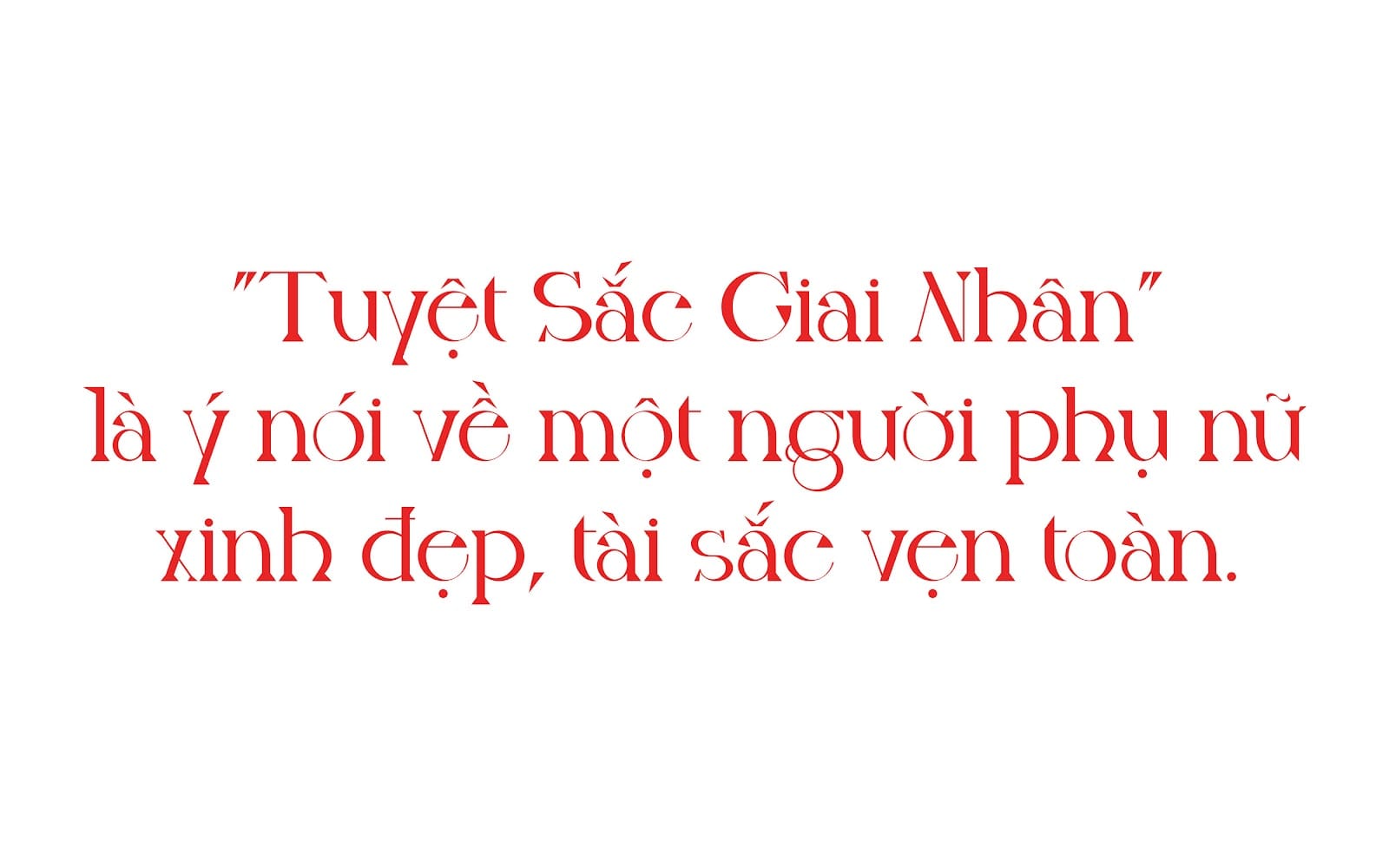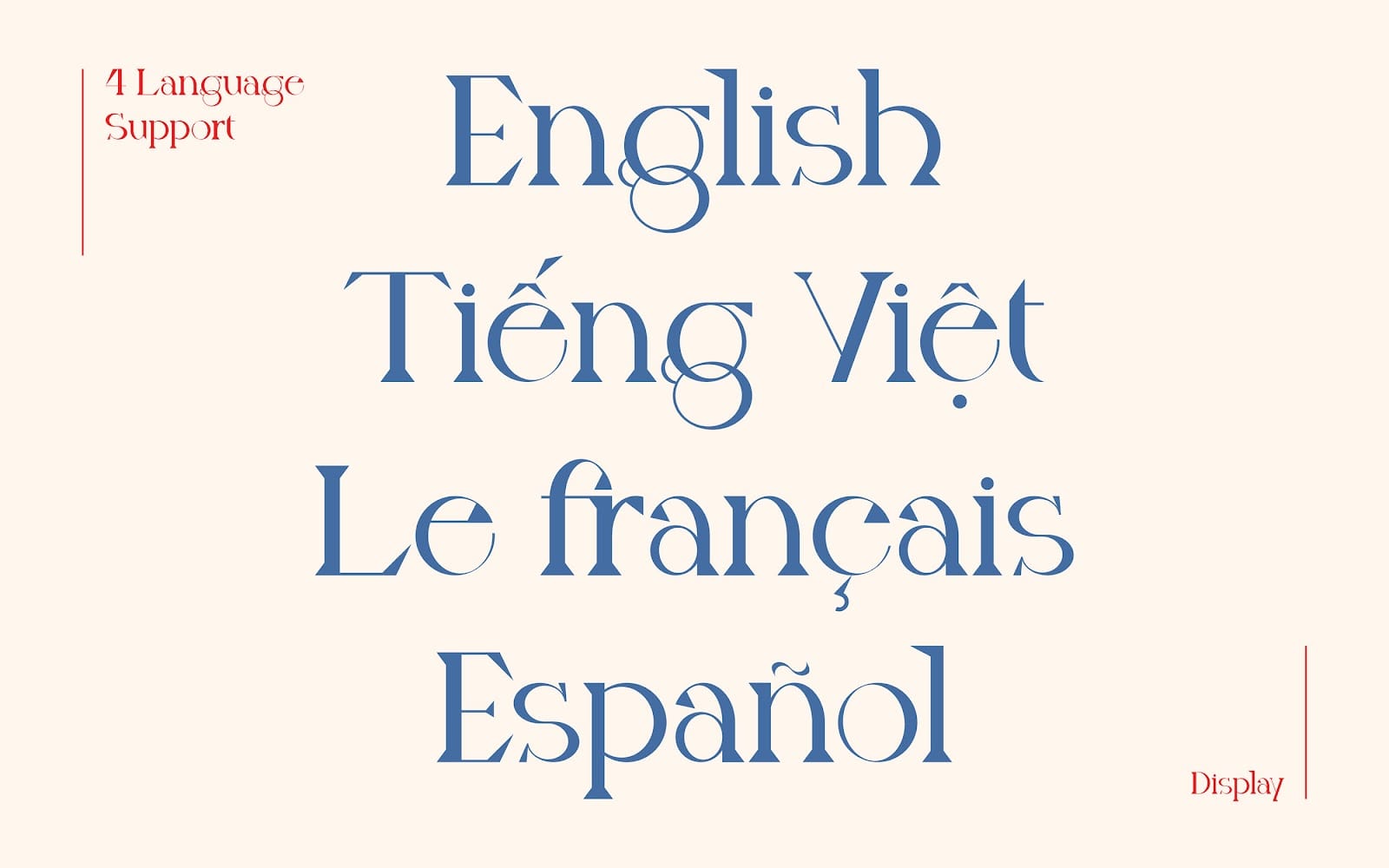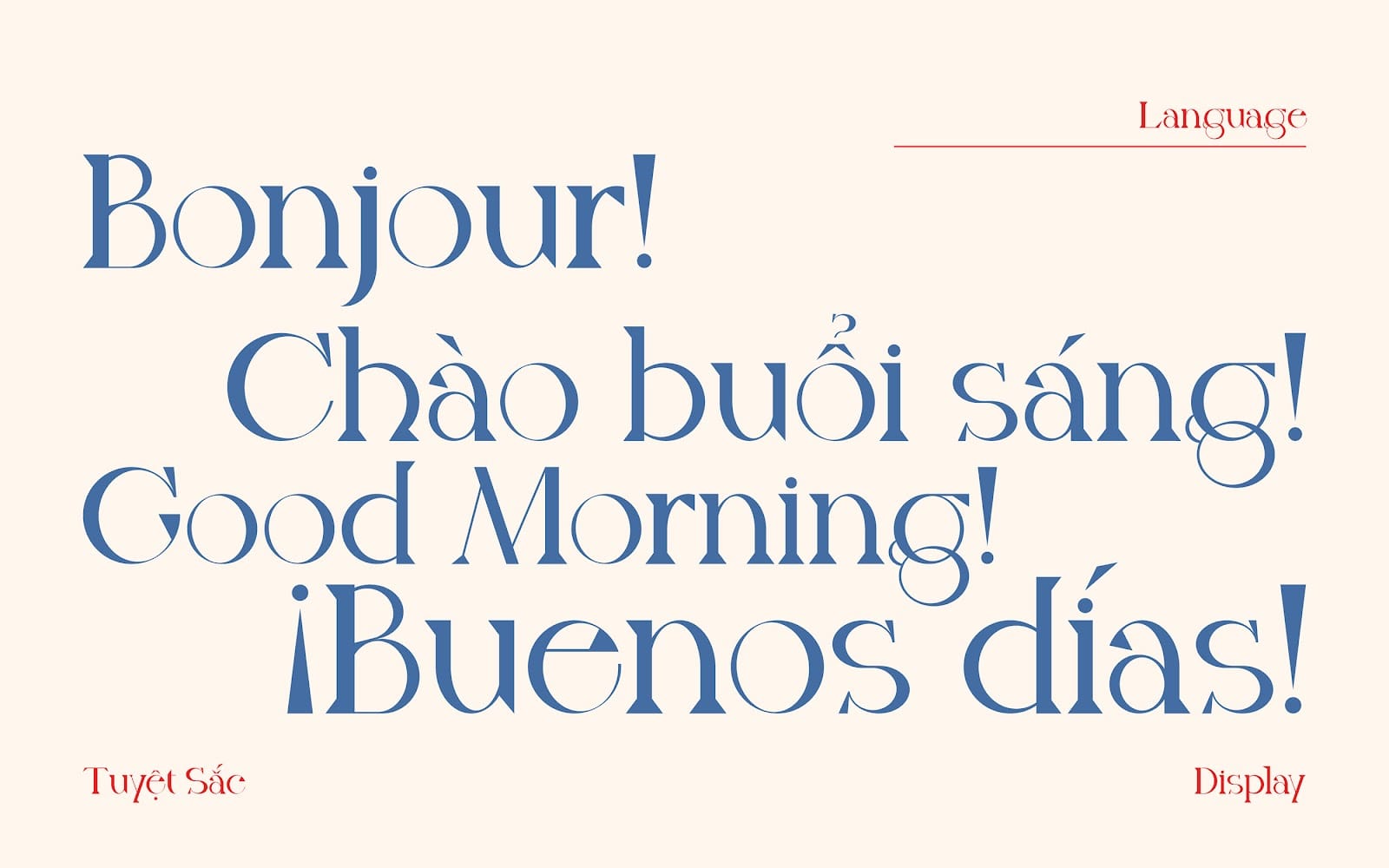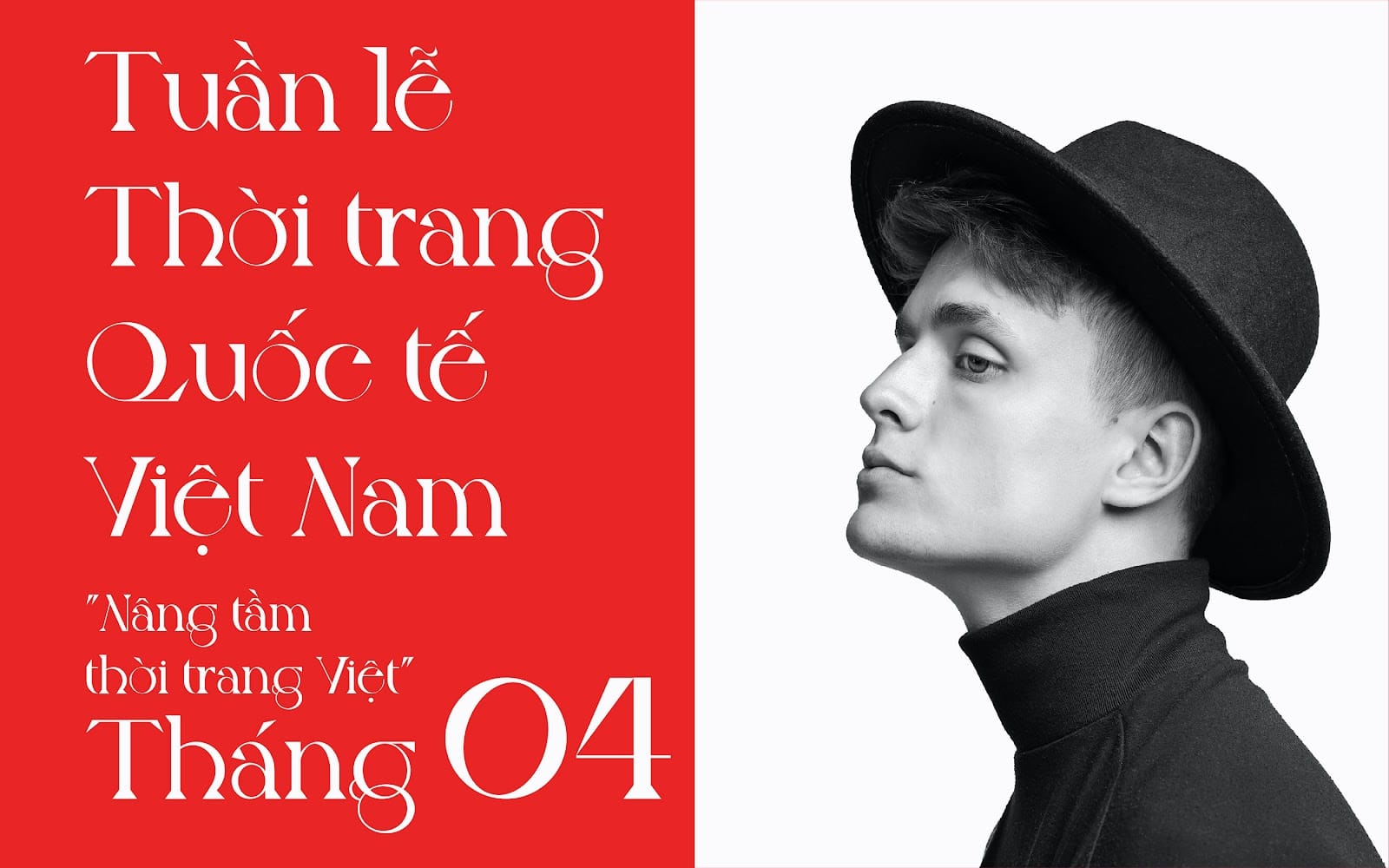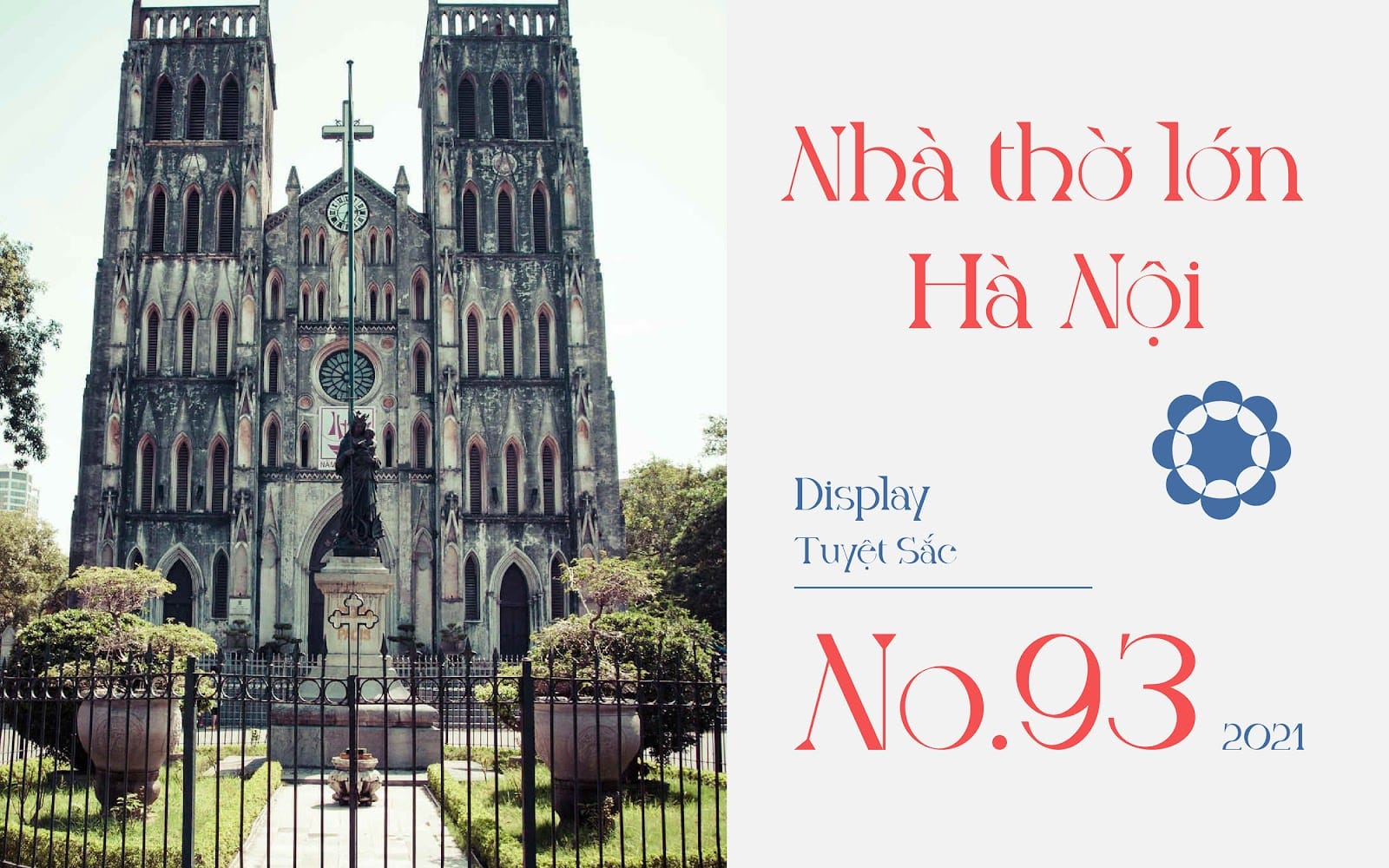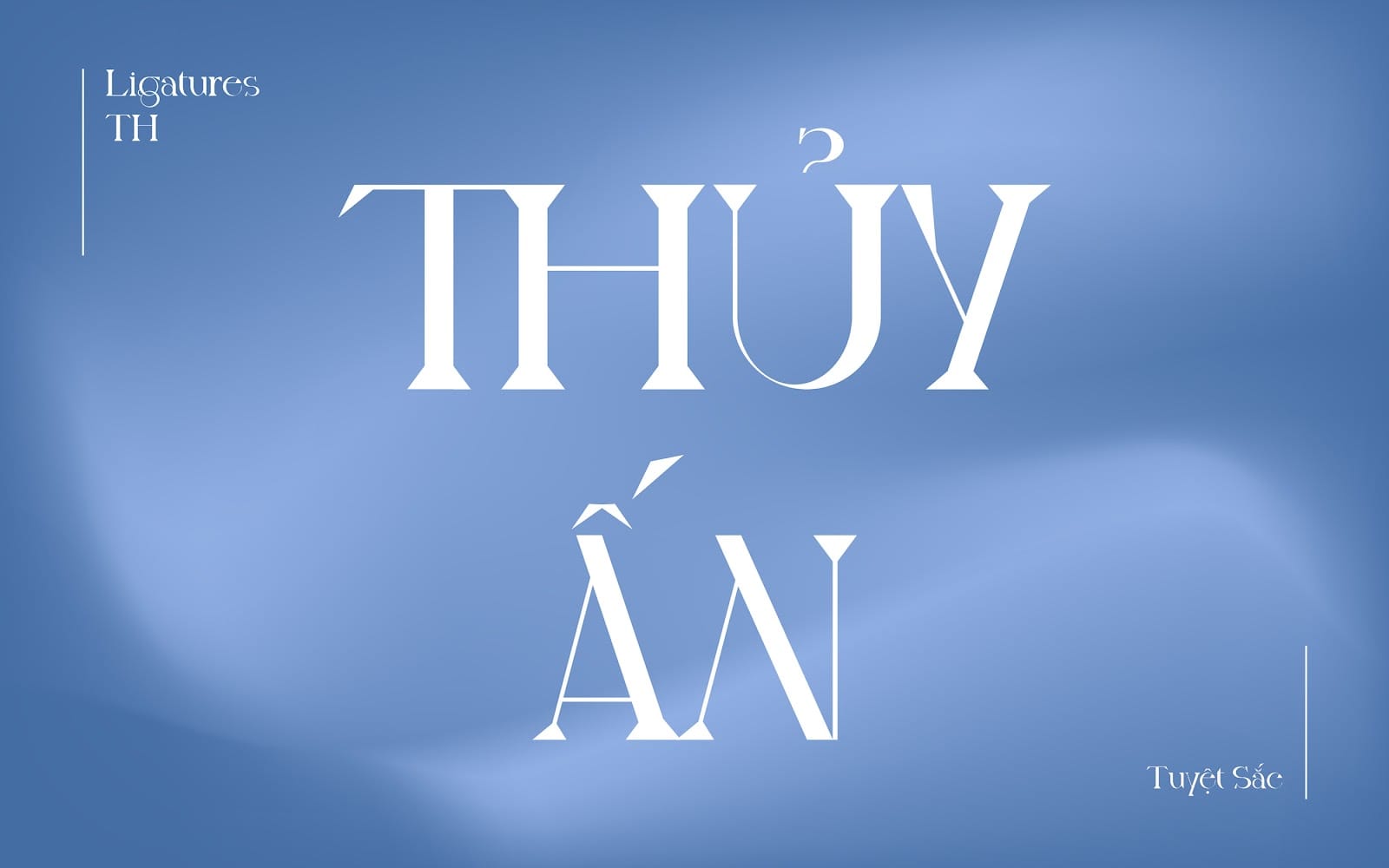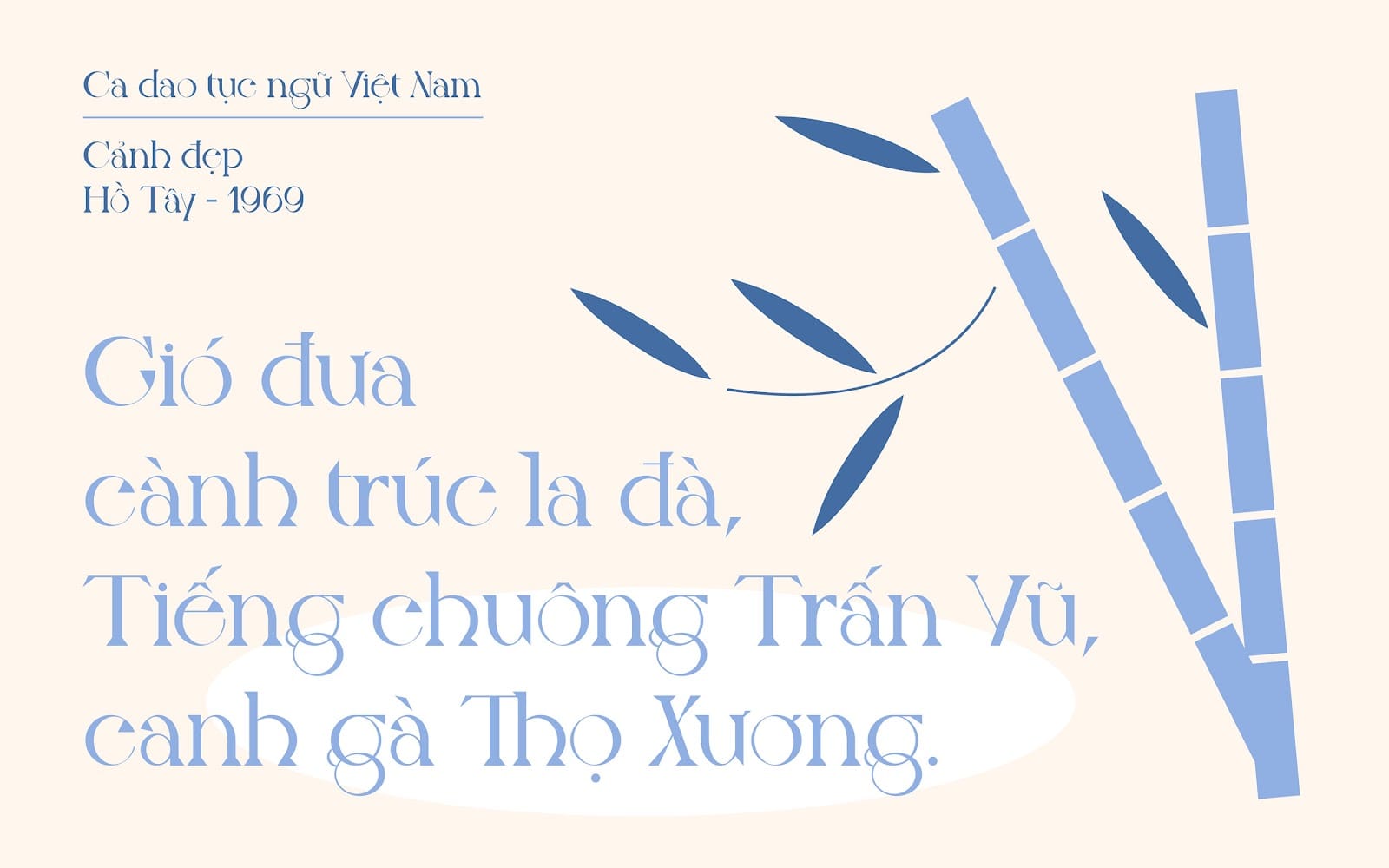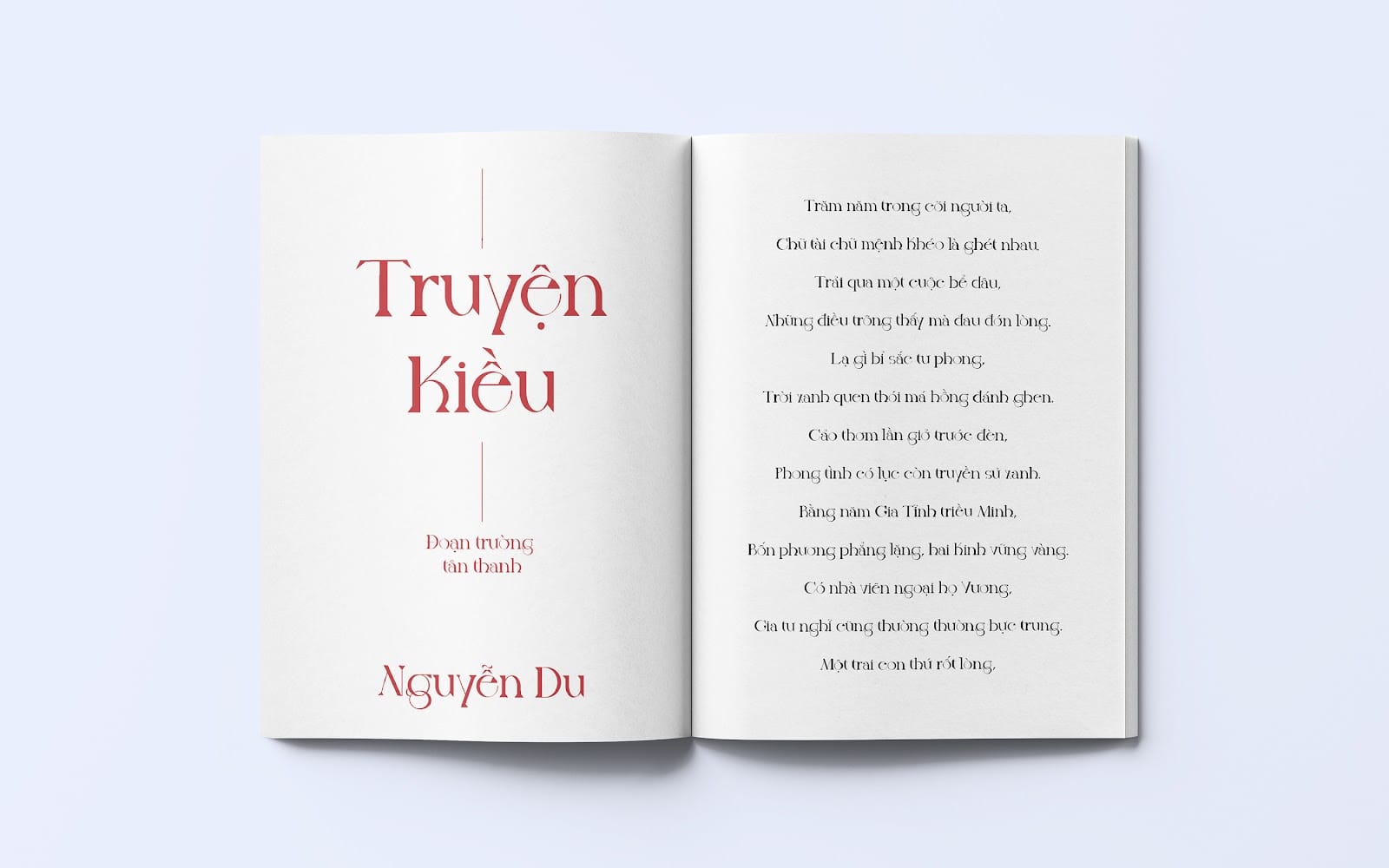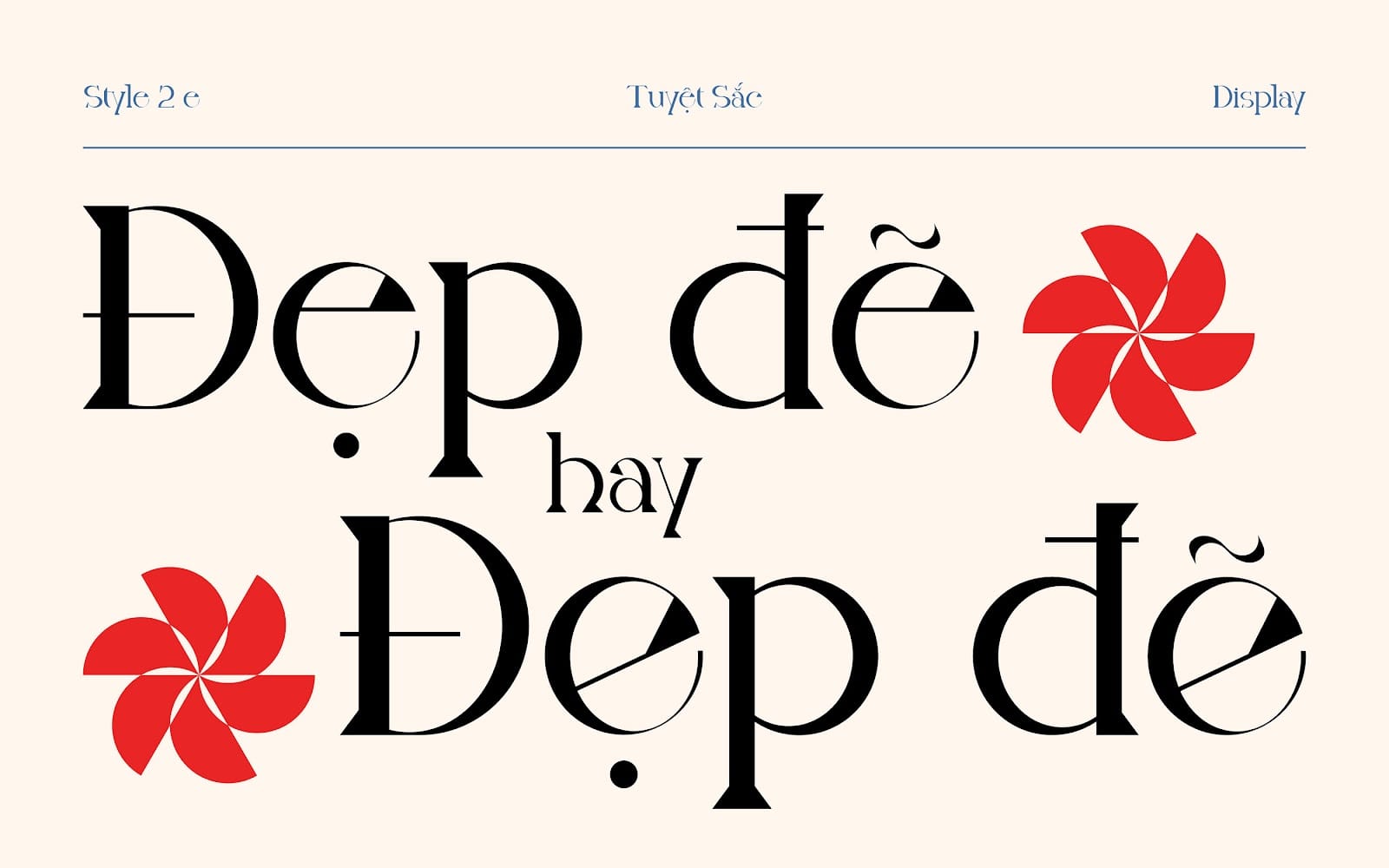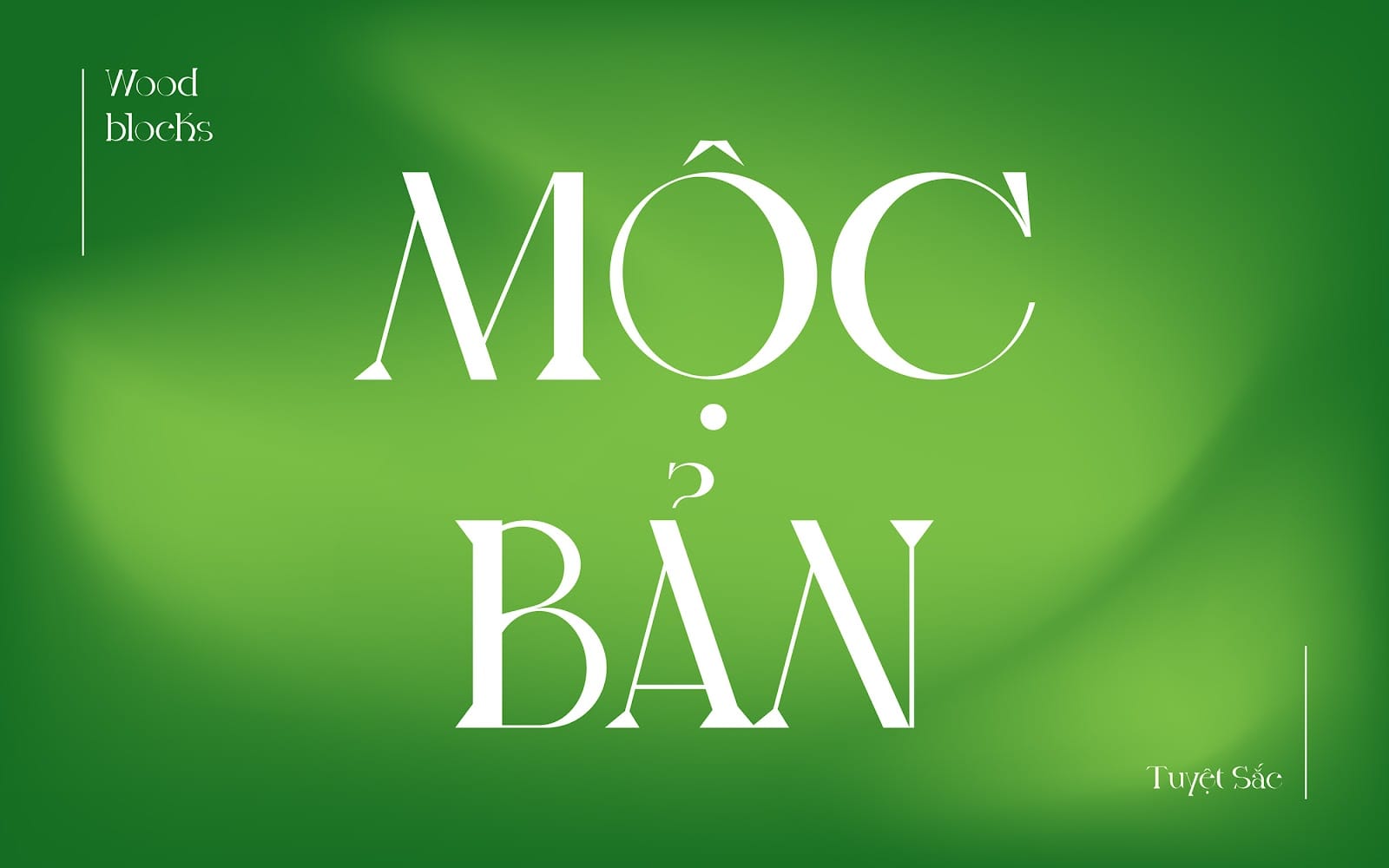
Font chữ Tuyệt Sắc được lấy cảm hứng từ “Tuyệt Sắc Giai Nhân”, một câu nói ám chỉ những người phụ nữ xinh đẹp và thông minh. Font chữ này được thiết bởi tác giả Cường Lưu.
Tuyệt Sắc – Type Face là một phông chữ serif với thiết kế kết hợp giữa Transitional và Neo Classical một phông chữ có các đường thẳng cơ bản, dễ nhận biết nhưng có độ tương phản rõ ràng và mềm mại. Font chữ mang đến sự sang trọng và lịch lãm và pha chút khỏe khoắn.
Font chữ Tuyệt Sắc mang lại một cảm giác hiện đại, thẩm mỹ và có một chút gì đó hoài niệm phù hợp với các tác phẩm cổ điển – hiện đại với sự sáng tạo và nổi bật trong từng nét chữ.